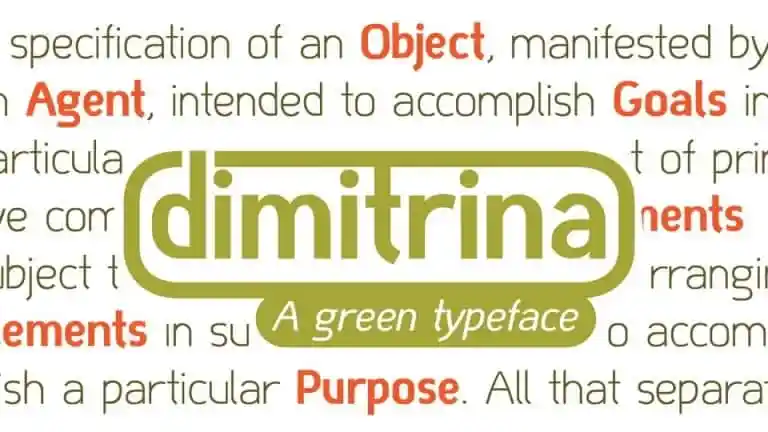
A Dimitrina Sans Serif é uma tipografia sem serif que se destaca por sua simplicidade e arredondamento delicado. Este tipo é perfeito para projetos visuais como logotipos, pois se adapta a diversas situações, seja em um site profissional ou em um adesivo de carro. Com letras maiúsculas e minúsculas, números e alguns caracteres especiais inclusos, a Dimitrina Sans Serif é uma escolha versátil para qualquer aplicação gráfica que necessite de uma fonte sem serif moderna e moderna. Seu design minimalista permite uma harmonia elegante entre o texto e a imagem, tornando-a uma opção perfeita tanto para projetos comerciais quanto para criações pessoais, garantindo um toque sofisticado em qualquer projeto visual.